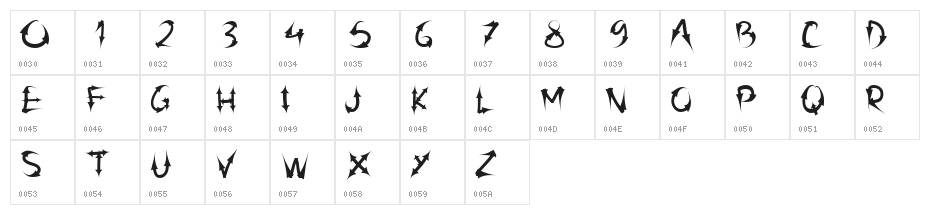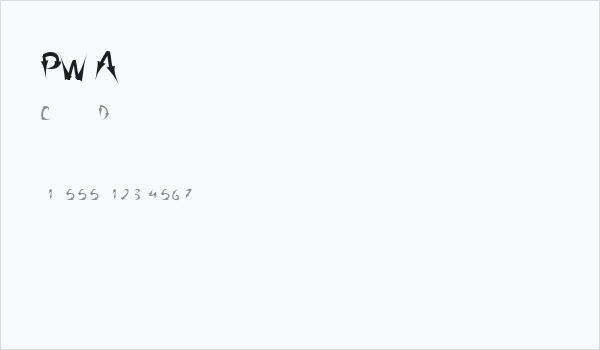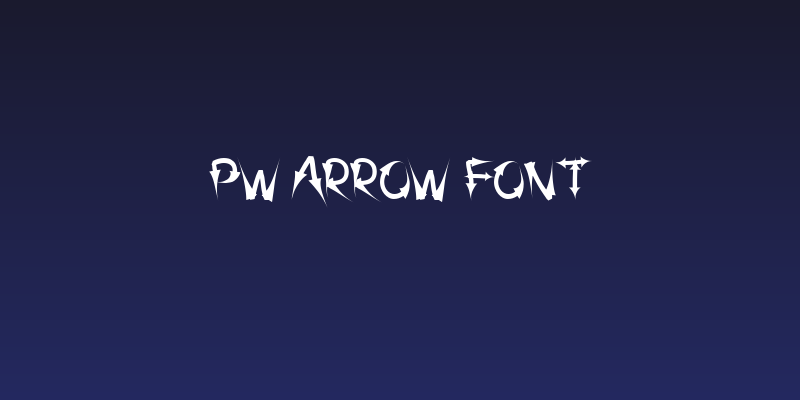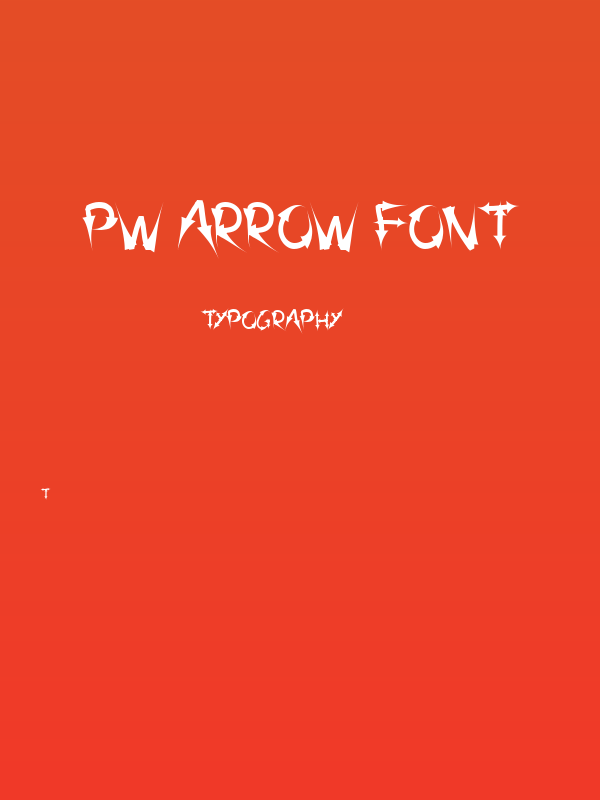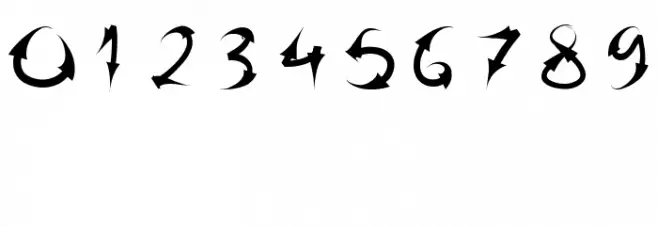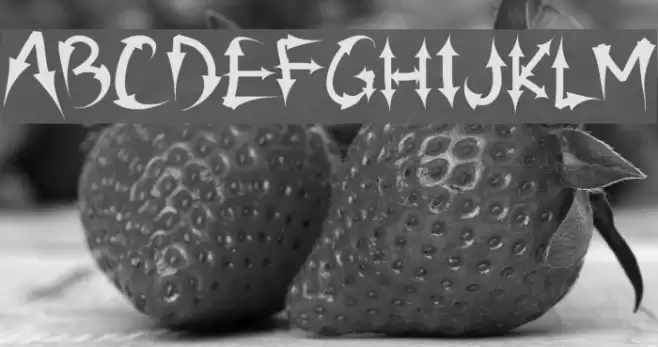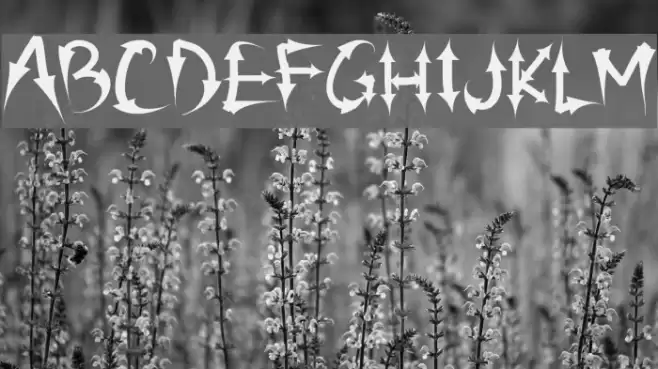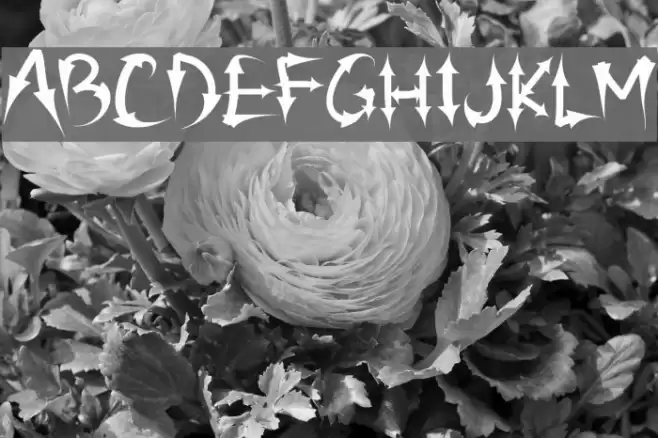
PW Arrow font Font
| Stil general | Modern, Edgy |
| Proiecte propuse | Ideal for action-themed posters, video game titles, branding for extreme sports, or any project needing a dynamic and edgy look. |